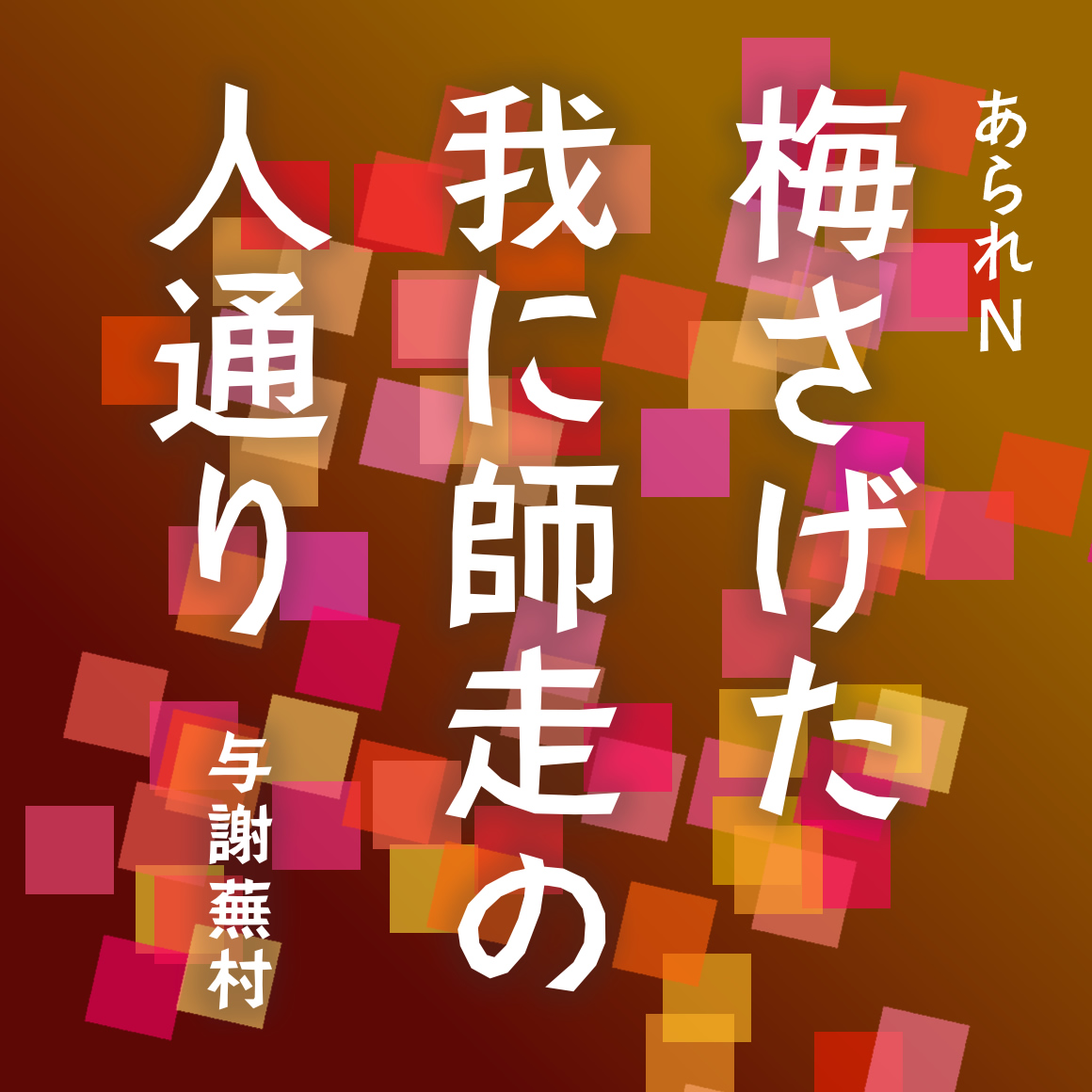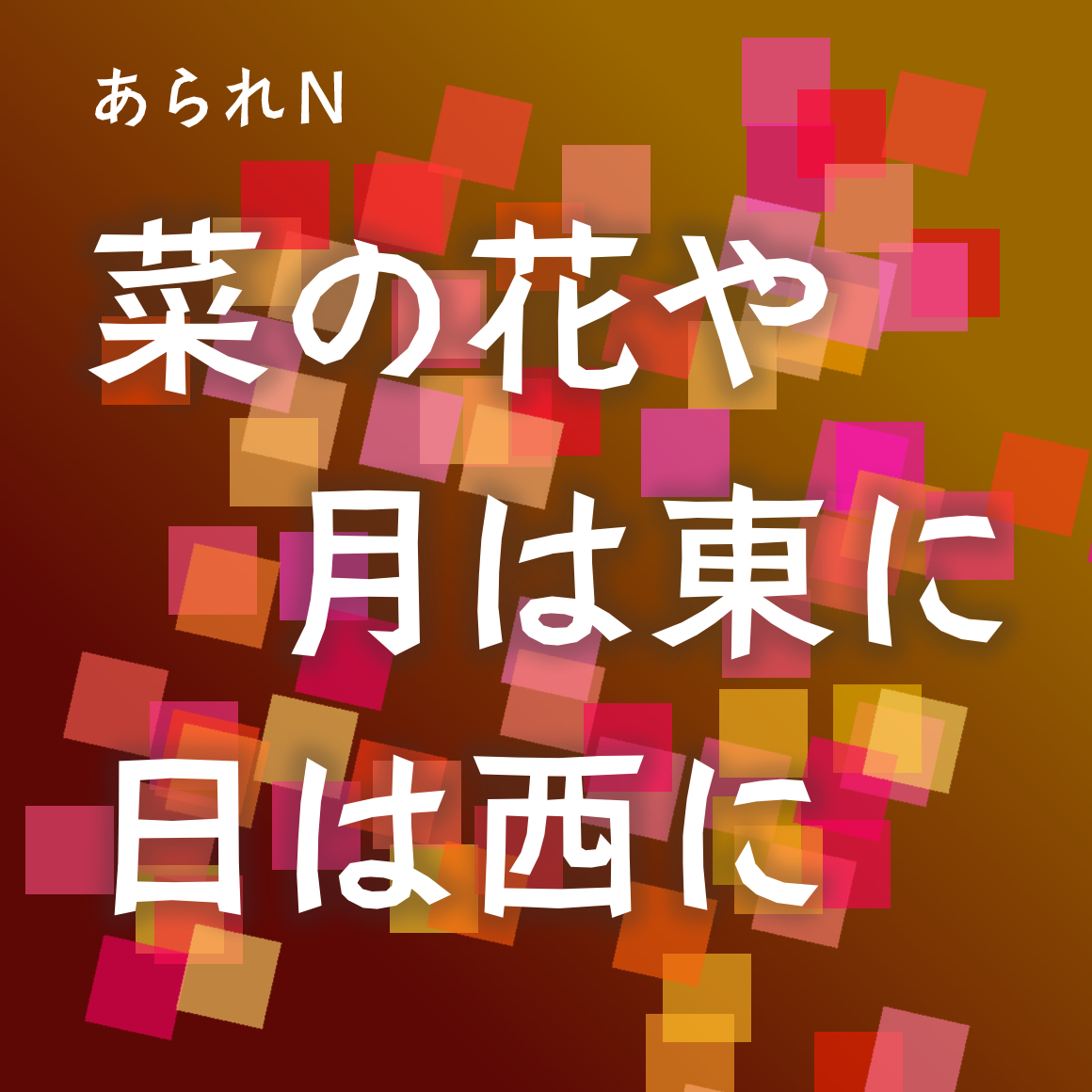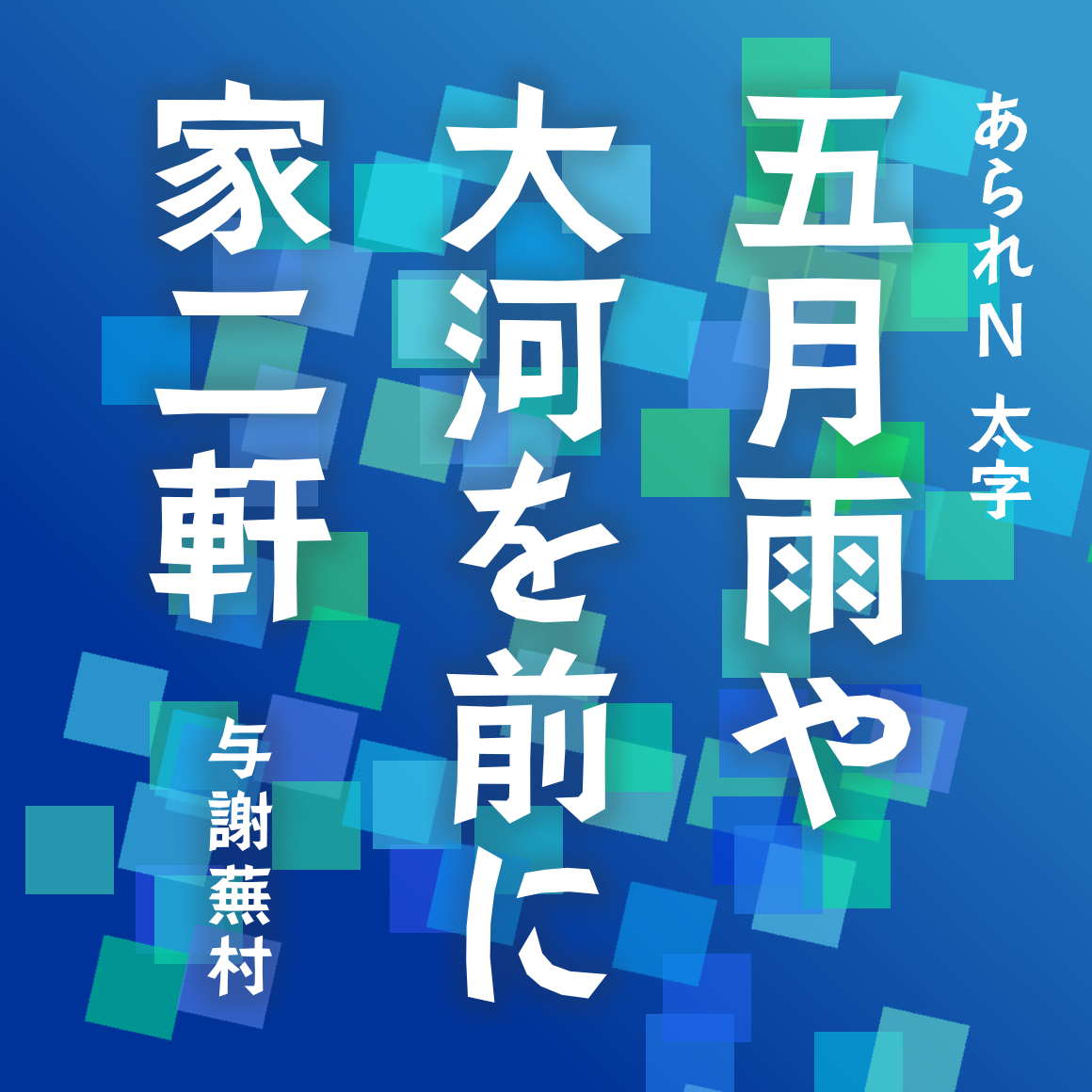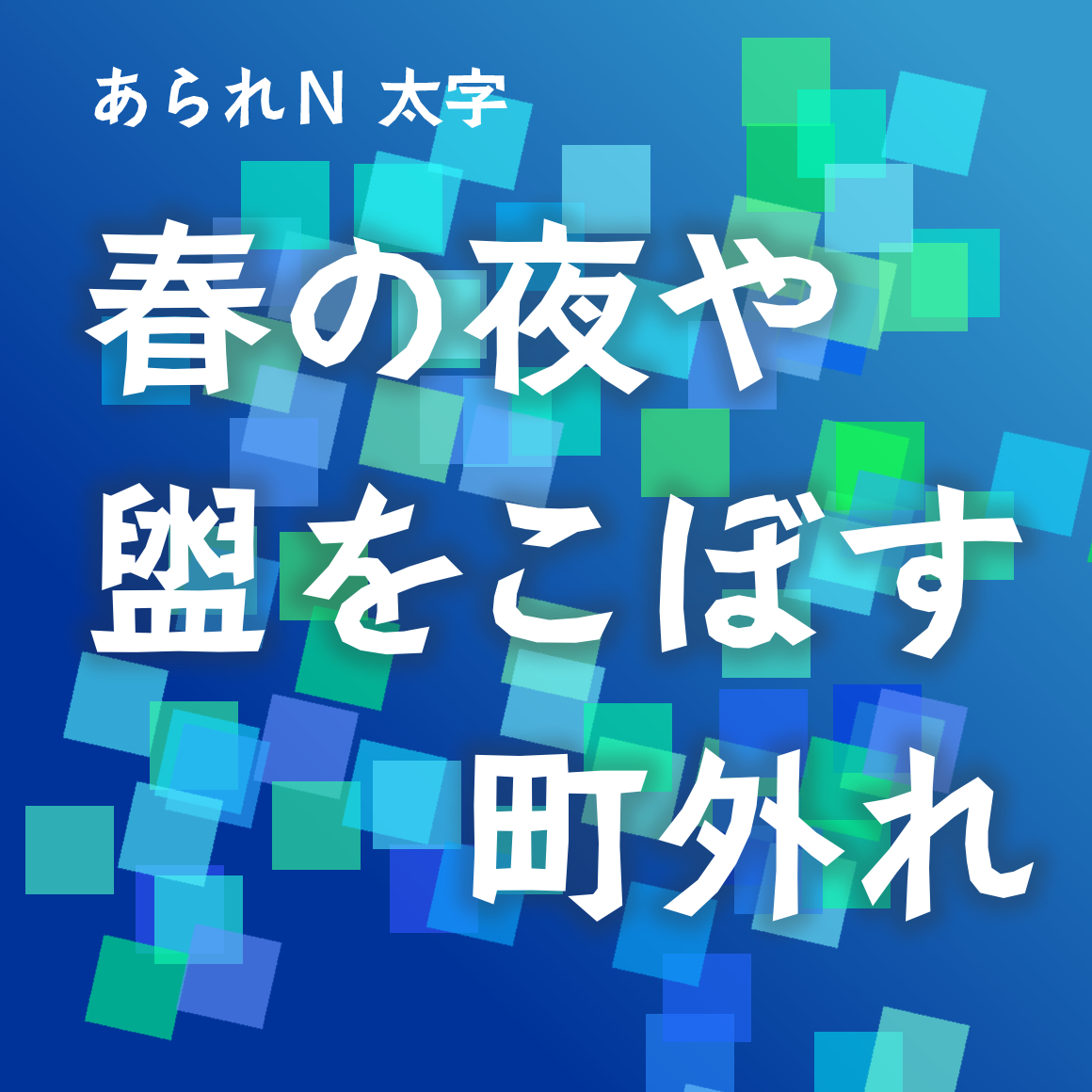
| デザイン |
切り絵や木版画のような素朴な味わいと、日本文字独特の情感を、直線だけでどのくらい表現できるか挑戦してみました。 |
連想されるイメージ |
素朴・伝統工芸・田舎・温かい・古風・味がある・懐かしい・小気味良い・和風・ハートフル・見た目スッキリ・優しい日本の風情・季節なら冬、色なら焦げ茶、酒なら焼酎・おいしそう・ほのぼの・日本昔話・寂しさ・あっさり・田舎の母・絵になる・手作り・庶民的・明治・大正ロマン作品に登場する女性たち…。 |
収容字種 |